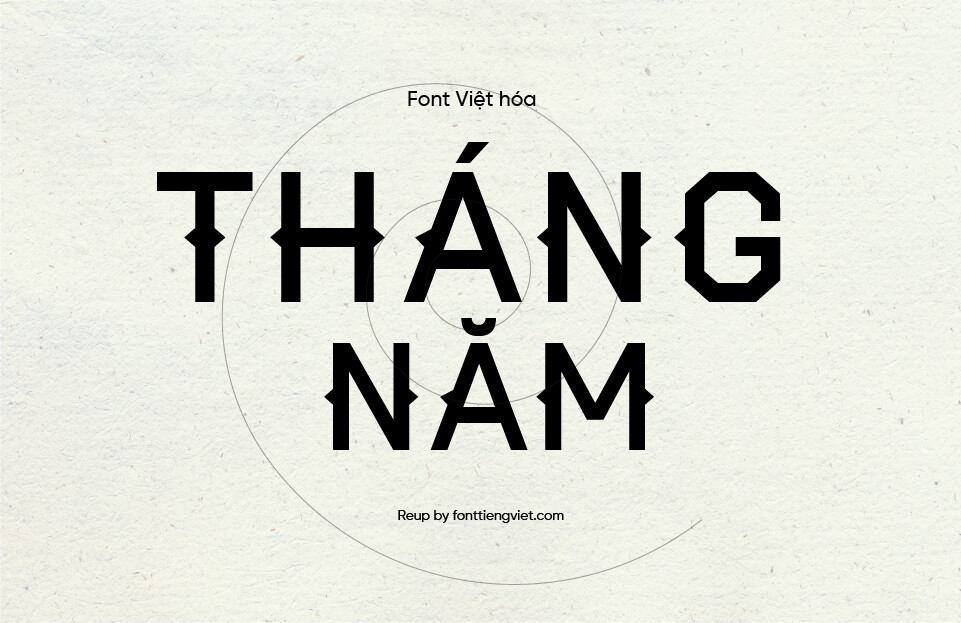
Font việt hóa UVF Haymaker
Tải Font việt hóa UVF Haymaker miễn phí cho thiết kế cổ điển
Giới thiệu về Font việt hóa UVF Haymaker
Trong thế giới thiết kế đồ họa hiện đại, việc lựa chọn một bộ Font Chữ phù hợp là yếu tố then chốt để tạo nên sự ấn tượng. Một trong những cái tên nổi bật nhất cho phong cách cổ điển chính là Font việt hóa UVF Haymaker. Đây là một bộ phông chữ lấy cảm hứng từ các bảng hiệu thủ công và chữ viết tay trên áo đấu thể thao cổ xưa. Với các đường nét mạnh mẽ, góc cạnh và có phần thô ráp, Haymaker mang đến hơi thở của sự hoài cổ nhưng vẫn giữ được nét tinh tế cần thiết cho các ấn phẩm truyền thông hiện nay.
Tại sao nên dùng Font việt hóa UVF Haymaker trong học tập
Đối với các bạn học sinh và giáo viên, việc sử dụng Font việt hóa UVF Haymaker giúp các bài thuyết trình hay báo cáo trở nên sinh động hơn. Phông chữ này đặc biệt hiệu quả khi dùng làm tiêu đề cho các chủ đề về lịch sử, thể thao hoặc các sự kiện ngoại khóa. Nhờ bản việt hóa chuẩn từ UVF, người dùng hoàn toàn không lo lỗi dấu khi đánh tiếng Việt, giúp văn bản luôn chuyên nghiệp và rõ ràng.
Đặc điểm nổi bật của bộ font này
Điểm độc đáo của Haymaker nằm ở cấu trúc chữ in hoa đầy bản sắc. Nó không chỉ đơn thuần là một kiểu chữ mà còn là một tác phẩm nghệ thuật với các chi tiết cắt xẻ độc đáo. Khi kết hợp với các tông màu trầm như nâu, vàng nghệ hay đỏ gạch, phông chữ này sẽ phát huy tối đa vẻ đẹp vintage của mình.
Ứng dụng thực tế của Haymaker
Bạn có thể dùng nó để thiết kế logo lớp, làm bìa sách hoặc trang trí các góc học tập. Sự linh hoạt giữa các nét đậm nhạt giúp người xem dễ dàng tập trung vào thông điệp chính mà bạn muốn truyền tải.
Kết luận về bộ font độc đáo